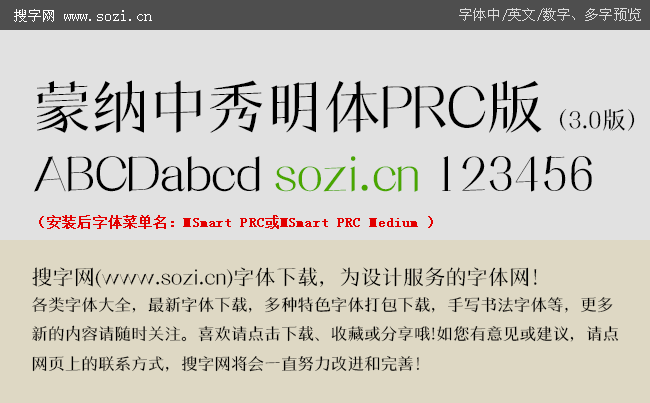
蒙納中秀明體PRC版
搜字網(wǎng)提供一款蒙納中秀明體PRC版中文藝術(shù)字體下載,蒙納中秀明體PRC版是一款棱角分明、個(gè)性突出的藝術(shù)字體,字體橫豎有點(diǎn)刀刻的味道,十分的鋒利大氣。可以應(yīng)用于廣告設(shè)計(jì)、平面設(shè)計(jì)、產(chǎn)品包裝、報(bào)刊雜志等領(lǐng)域。